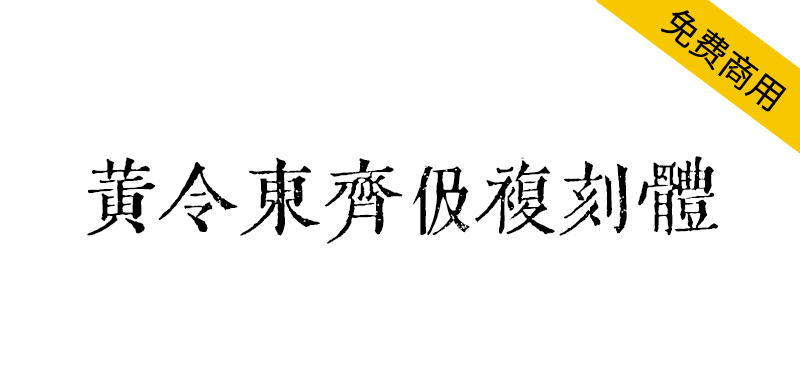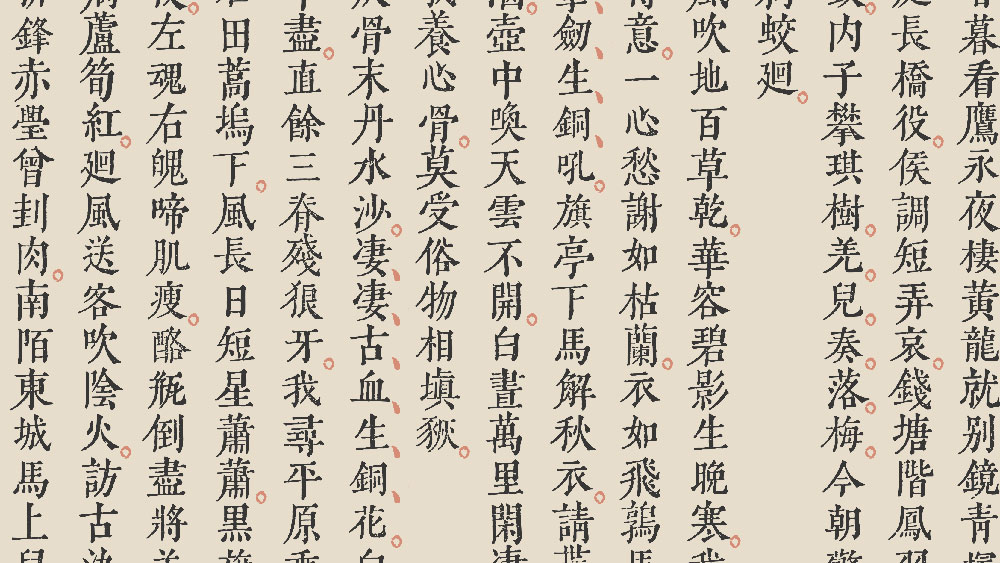
黄令东齐伋复刻体(QIJIC),基于古籍进行处理而得到的字体,所以只有繁体字形,采用半自动计算机视觉和OCR对《李長吉歌詩》和《淮南鴻烈解》进行扫描,通过程序处理后再手动选择适合的字型,最后导出成字体文件。
在使用字体的过程中,如果输入简体字,会直接映射成繁体字形,比如说你输入“国”字,出来的结果会是“國”字。